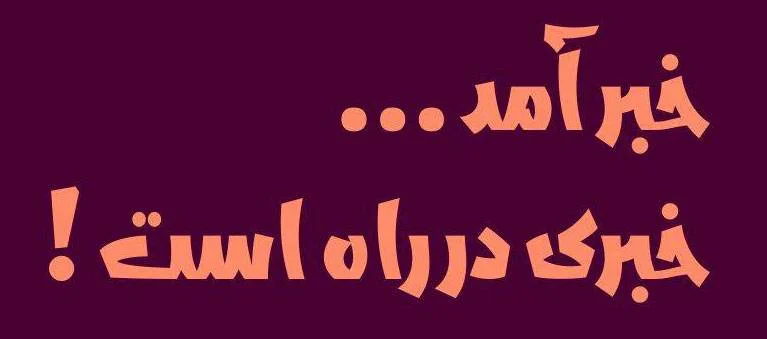
فونت قاف
طراح طراح فونت
• قلم فارسی قاف دارای حروف انگلیسی متناسب است.
• فونت قاف دارای کنتراست و ضخامت مناسب است.
• این فونت دارای اعراب گذاری هوشمند برای هر حرف می باشد.
• این فونت دارای جایگزینهای متنوعی برای زیبایی و خوانایی بهتر در متون می باشد.
• این فونت از زبان کردی بصورت کامل پشتیبانی میکند .
فونت فارسی قاف یک فونت نمایشی، هندسی و فانتزی در دسته فونت های جدید می‌باشد که از روی یک فونت دمو عربی به نام ابدو توسط گروه دیجی فونت باز طراحی و برای زبان فارسی و زبان فونت کردی بهینه شده است .تغییر در ساختار حروف، اضافه شدن کاراکترهای زبان کردی و جایگزین های متنوع برخی از تغییراتی است که در فونت قاف صورت گرفته است.